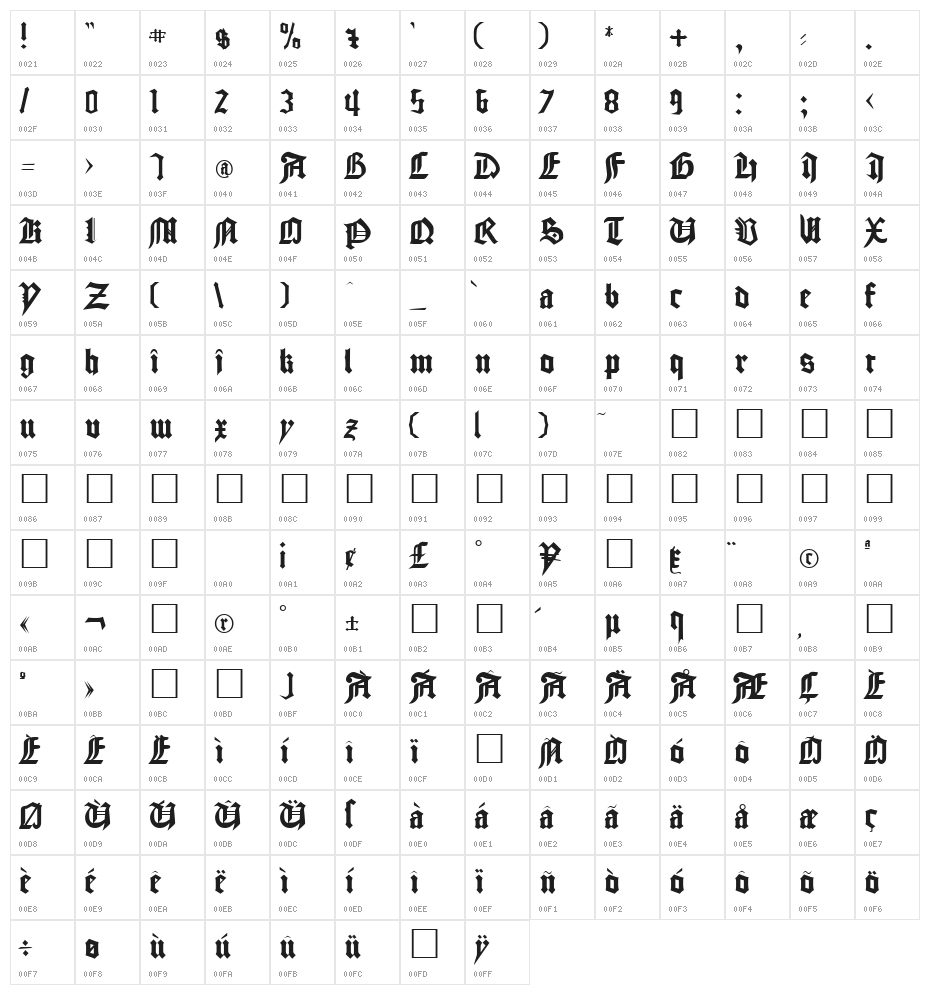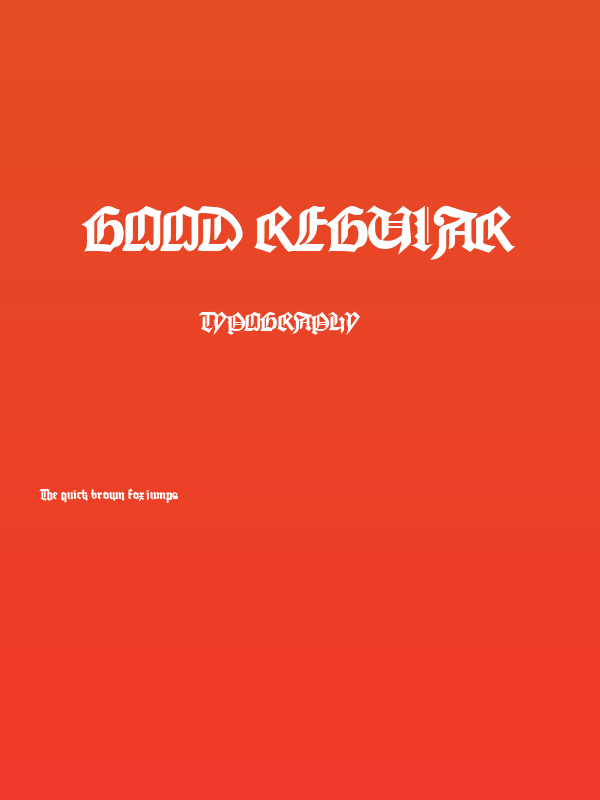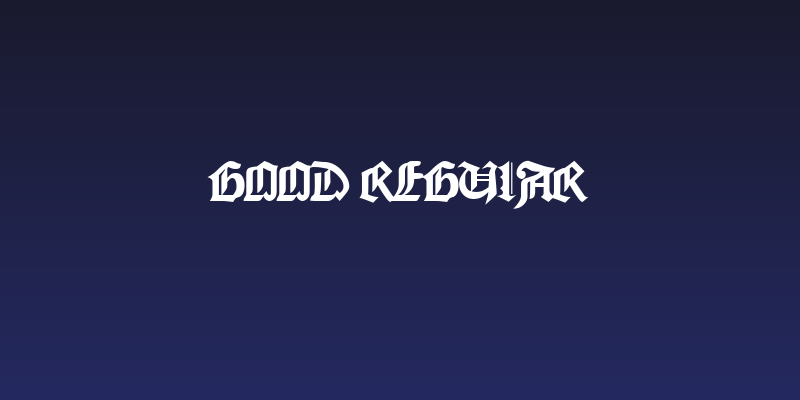
Good Regular Font
✎ Gothic
| Kategorien | Gothic |
| Gesamtstil | Classic |
| Anwendungsfall | Headlines, Logos, Certificates |
| Vorgeschlagene Projekte | Ideal for certificates, historical documents, branding for luxury products, or any project that requires a classic and formal touch. |